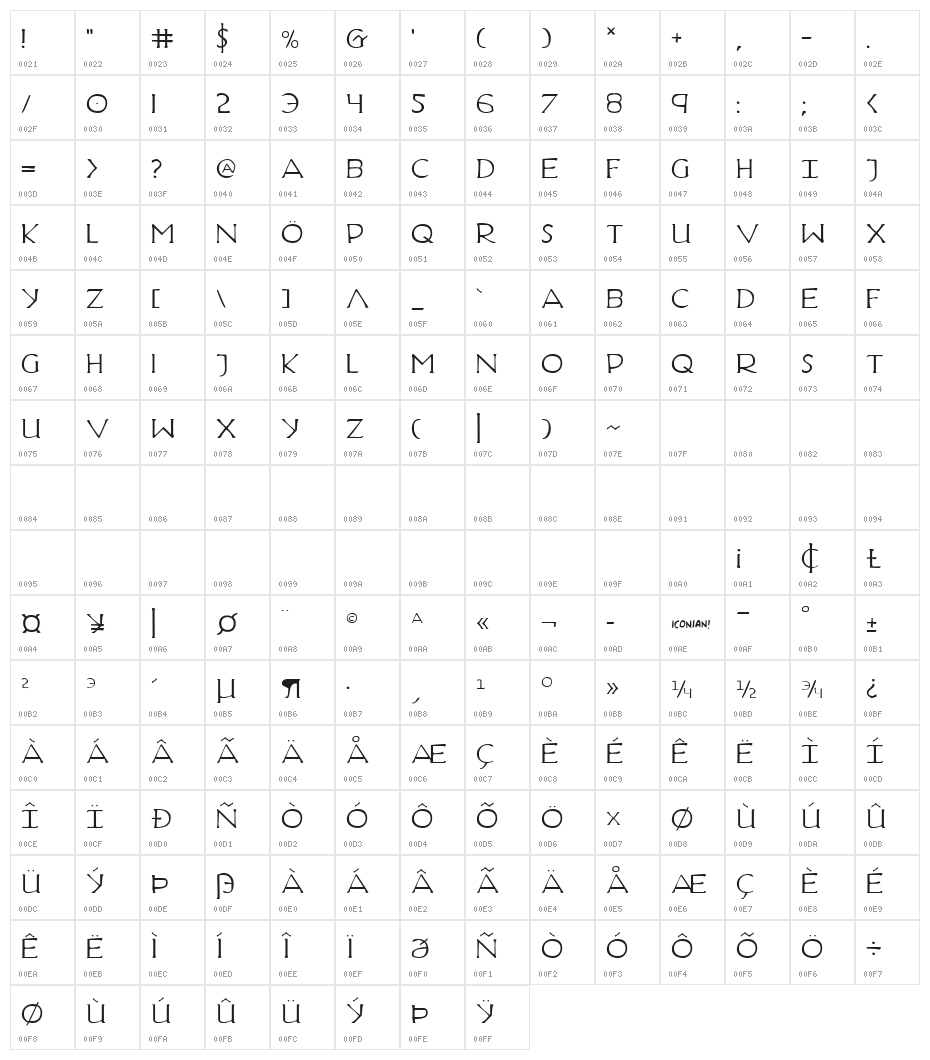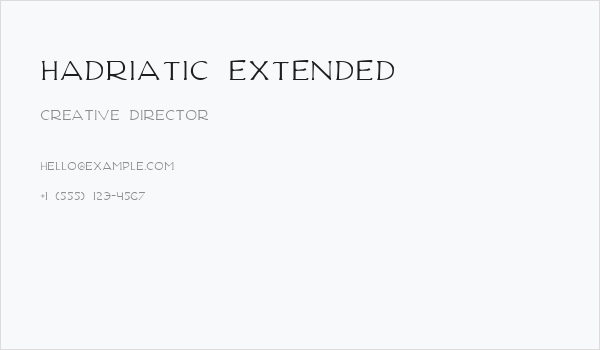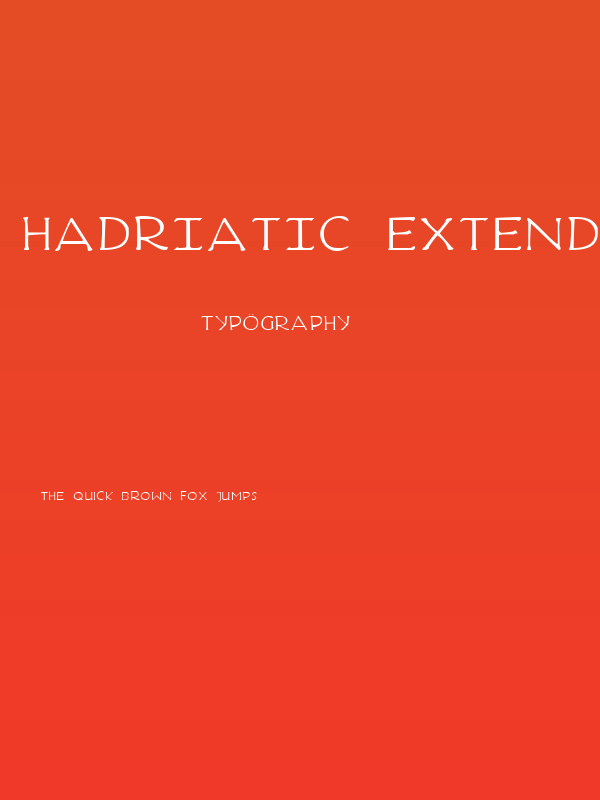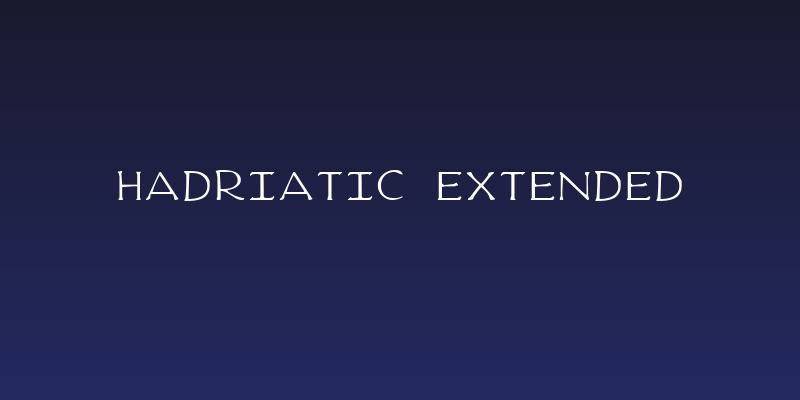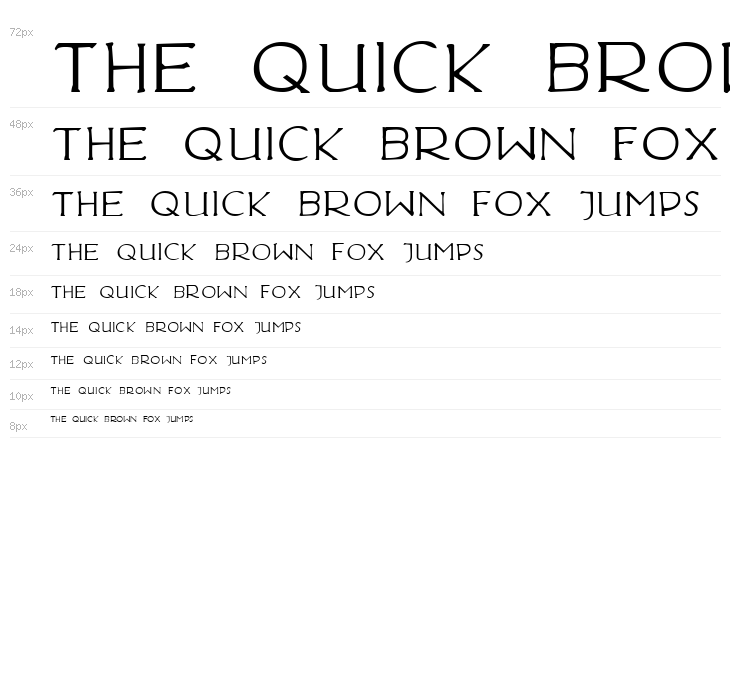
Hadriatic Extended Font
| Larghezza | Expanded |
| Caso d'uso | Headlines, Logos, Branding |
| Progetti proposti | Ideal for branding, headlines, posters, and editorial design where a modern yet classic look is desired. |
Hadriatic Extended